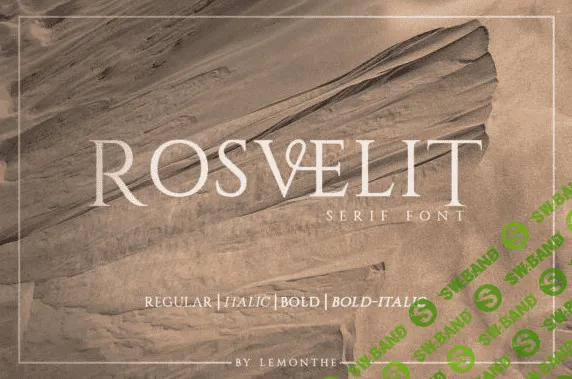
Название: Rosvelit Font
Рузвельт - это простой, но невероятно элегантный шрифт с засечками.
Его можно легко сопоставить с невероятно большим набором проектов, поэтому добавьте его к своим творческим идеям и обратите внимание, как он выделяет их!